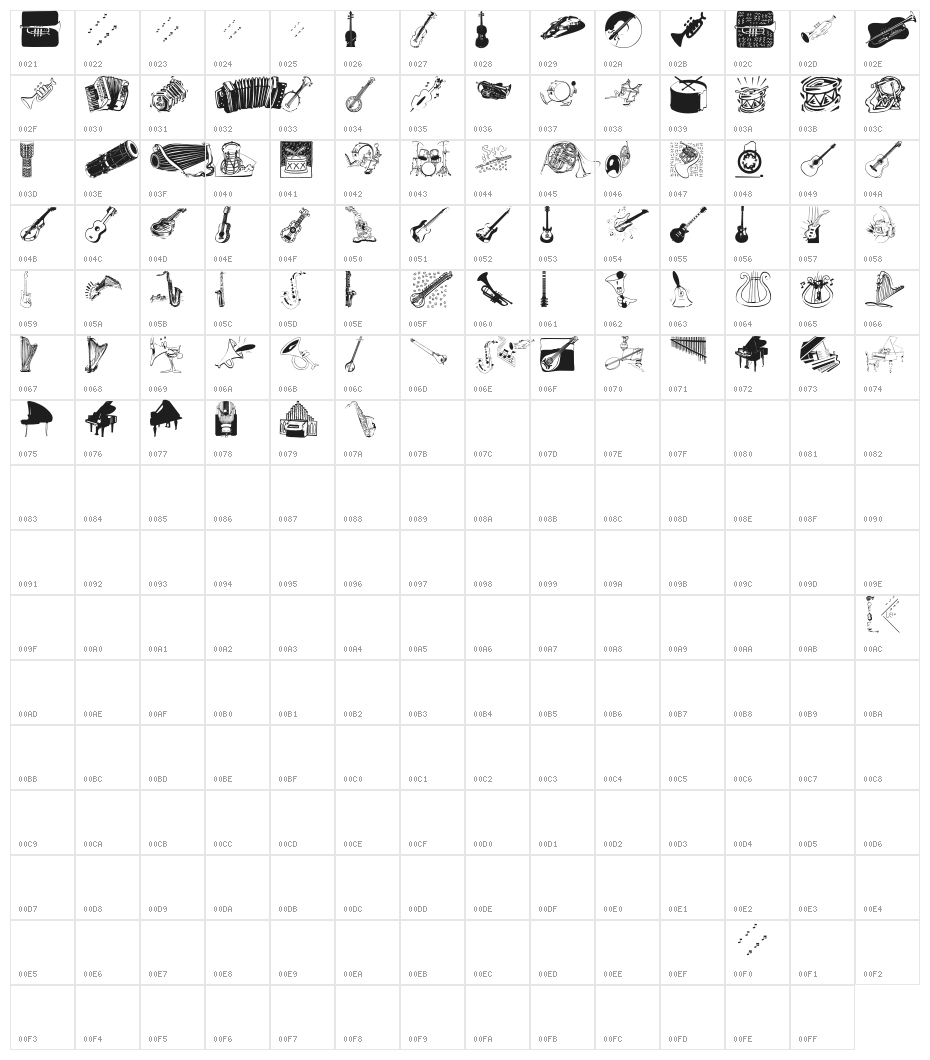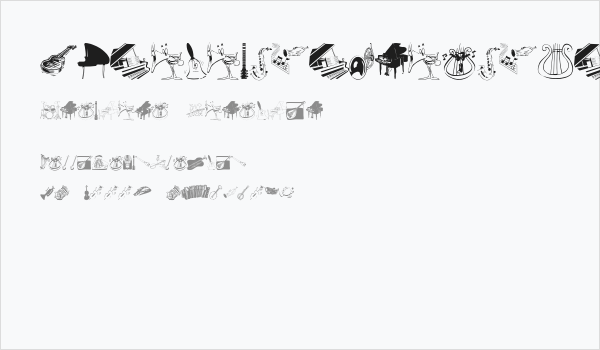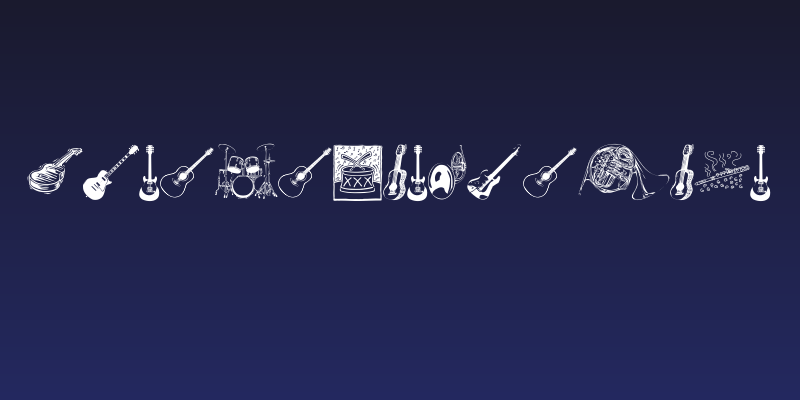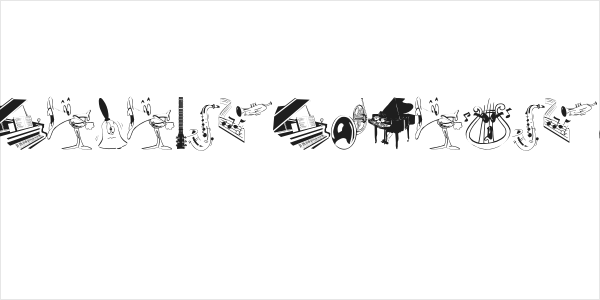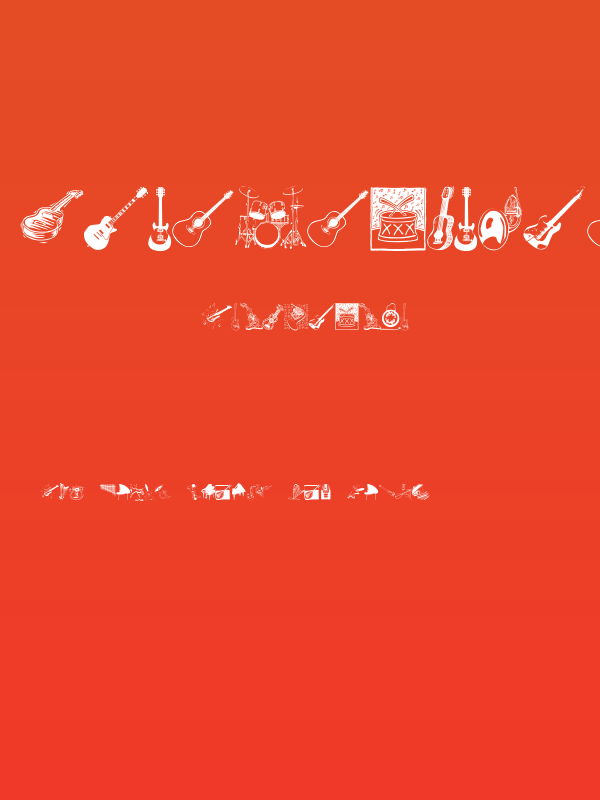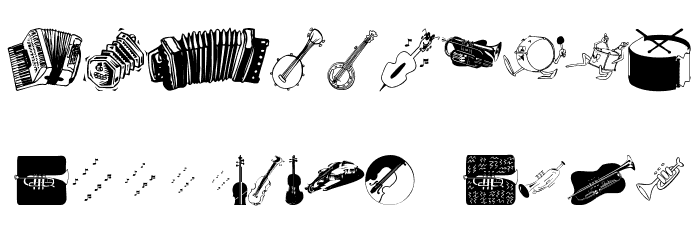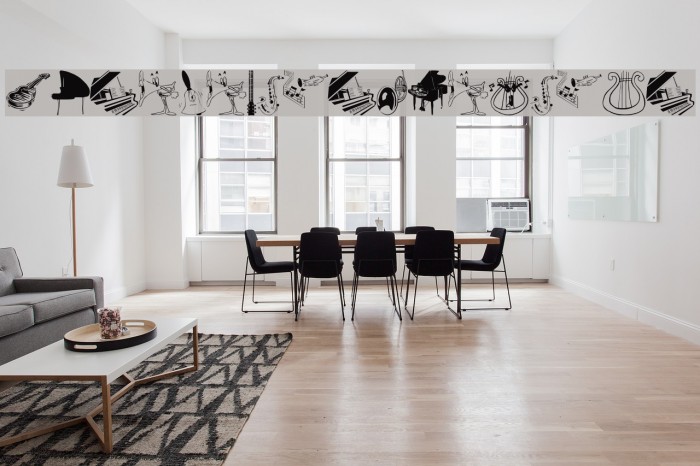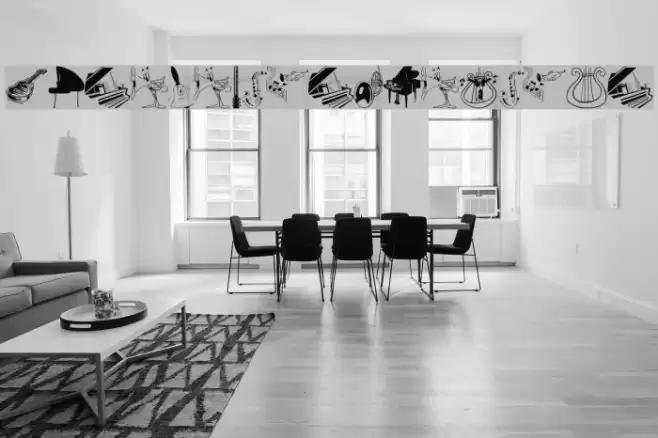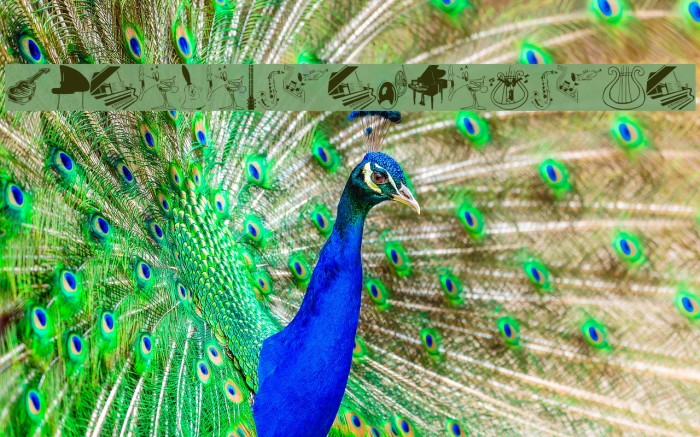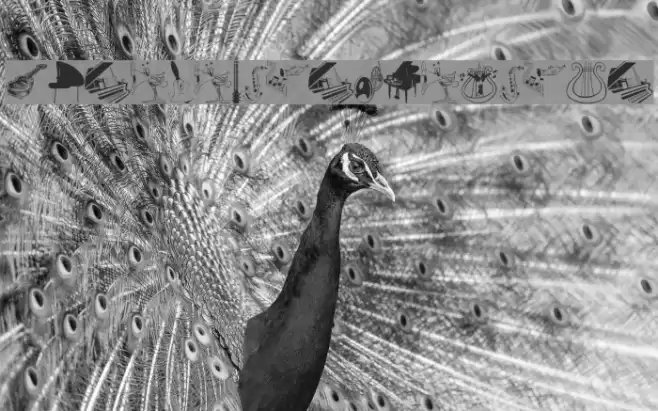
MusiciansFriends Font
| Stile generale | Decorative, Playful, Artistic |
| Caso d'uso | Headlines, Logos, Posters, Themed Graphics |
| Progetti proposti | Music event posters, children's educational materials, themed invitations, album covers, creative branding for music-related businesses. |